Griechische Schrift
Das griechische Alphabet ist eine der einflussreichsten Schriften der Weltgeschichte. Aus dem phönizischen Konsonantenalphabet hervorgegangen, fügte es als erstes echte Vokale hinzu — die Grundlage fast aller späteren europäischen Schriften.
Alpha bis Omega
Mutter der Alphabete
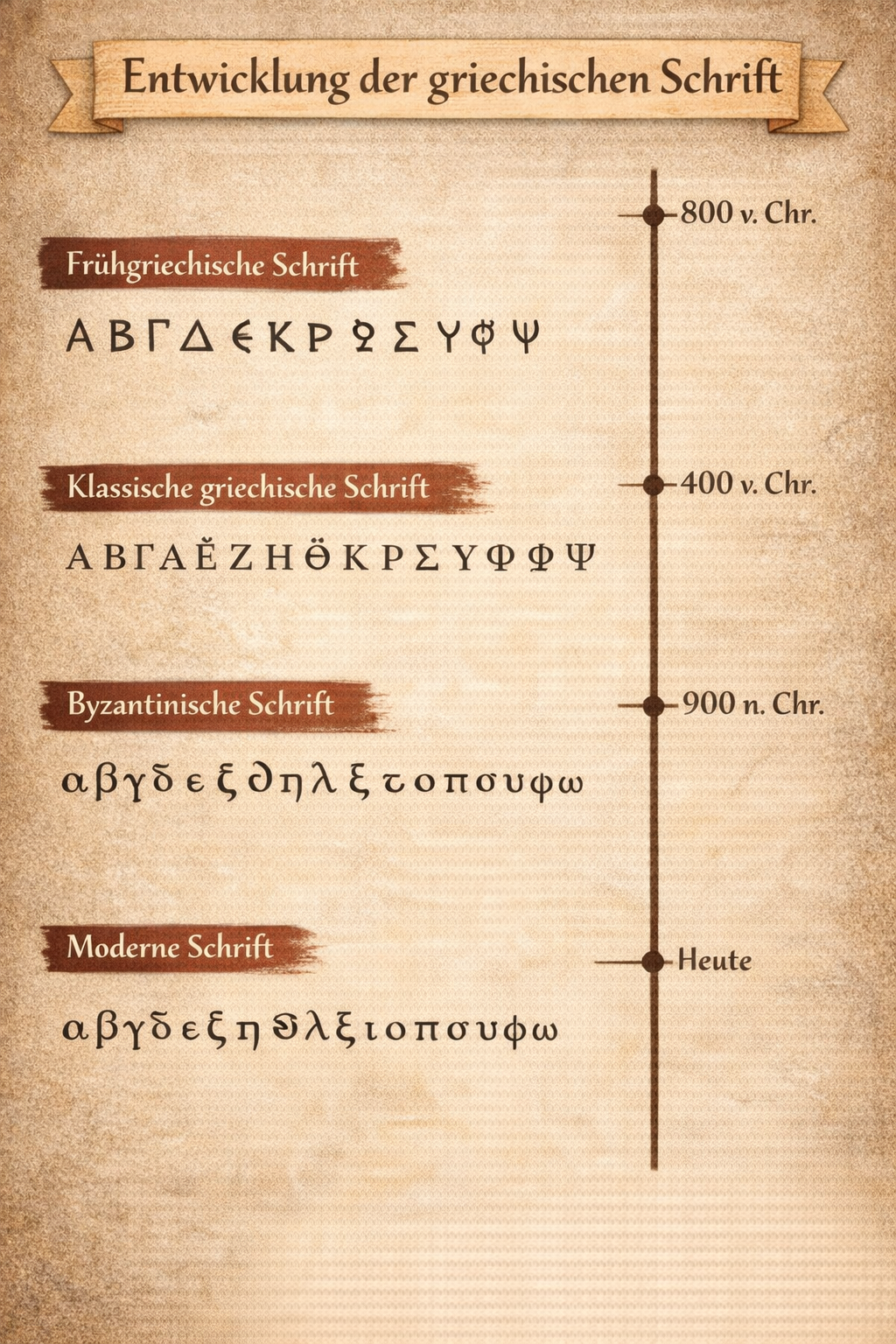
Ab 800 v. Chr.
Vom Phönizischen zum Hellenischen
Die Griechen übernahmen die phönizischen Konsonantenzeichen und gaben einigen davon Vokalwerte — eine kleine Änderung mit großer Wirkung. In Teilen findet sich das griechische Alphabet bis heute im Lateinischen, Kyrillischen und in der Mathematik wieder.